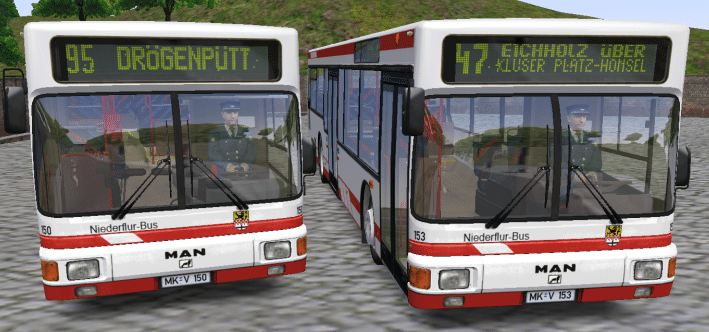
Hier bekommt ihr zwei verschiendene neue Lawo Fonts für die Omsi 2 Vollmatrix, welche im NL202, NG272 sowie im Citaro V2 und Citaro G verbaut ist.
Die Versionen unterscheiden sich folgendermaßen:
Version 1 "LLE" (rechts im Bild):
-Liniennummer vorne fett
-Liniennummer seitlich und hinten normal in "TST.F16"
Version 2 "Lawo" (links im Bild):
-Liniennummern alle schmal
Die Zielfonts beider Versionen sind gleich. Es sind lediglich Großbuchstaben enthalten.
Die Fonts bringen folgende Sonderzeichen mit sich:
Kaffeetasse (Ibis Code xxx41)
Tramsymbol (Ibis Code xxx43)
P+R Symbol (Ibis Code xxx42)
Loksymbol (Ibis Code xxx44)
Schwimmsymbol (Ibis Code xxx45)
großes S für SchnellBus-Linien (Ibis Code xxxx5)
Alle Sonderzeichen werden sowohl vorne, als auch seitlich und hinten angezeigt.